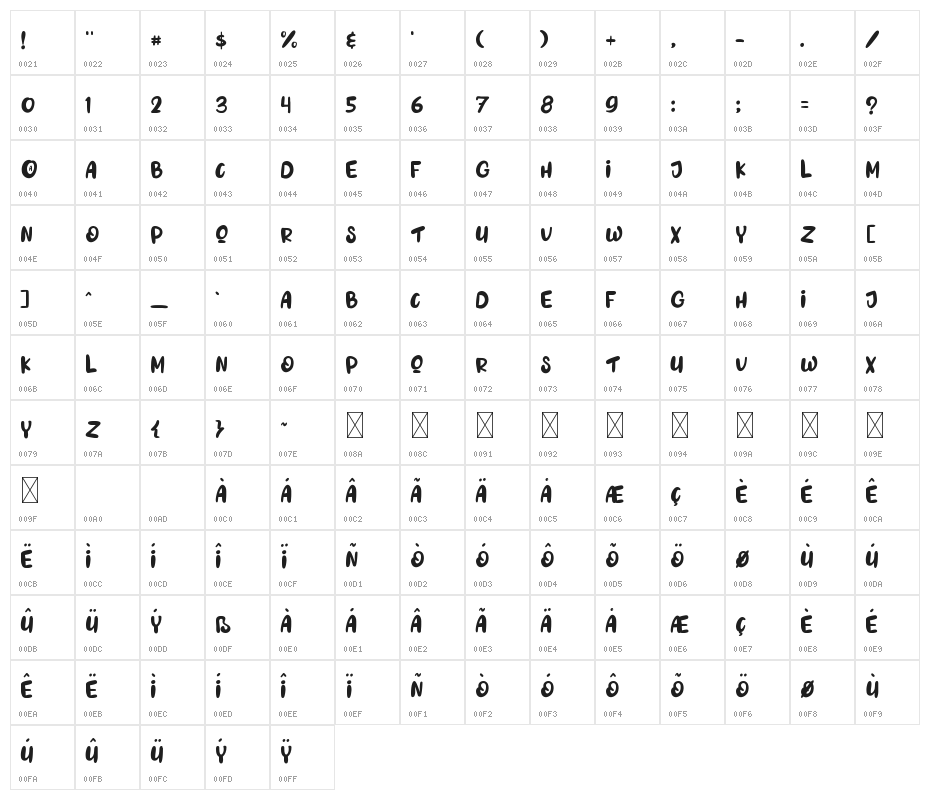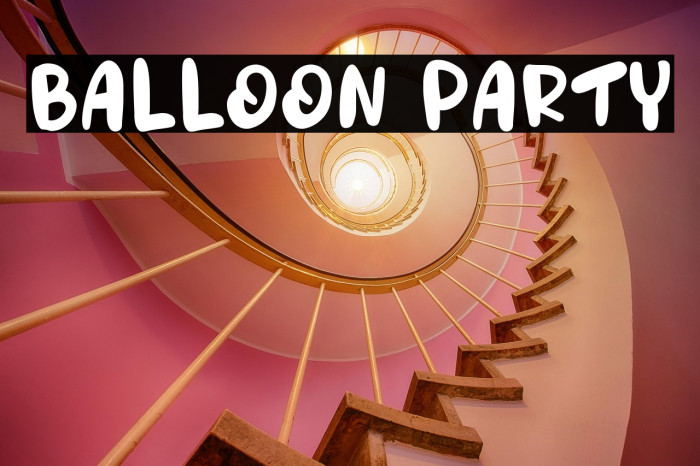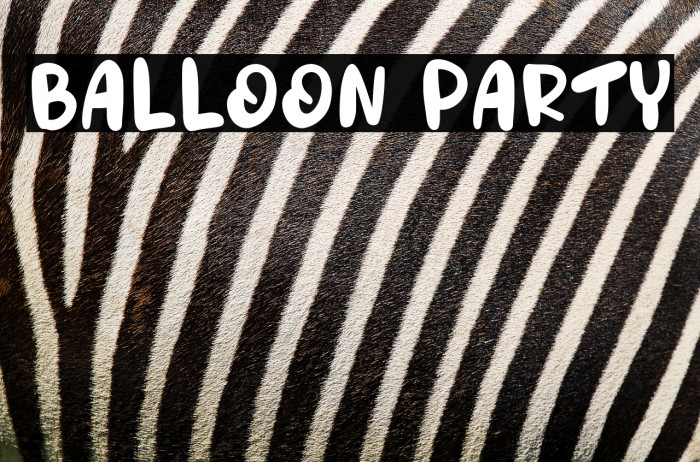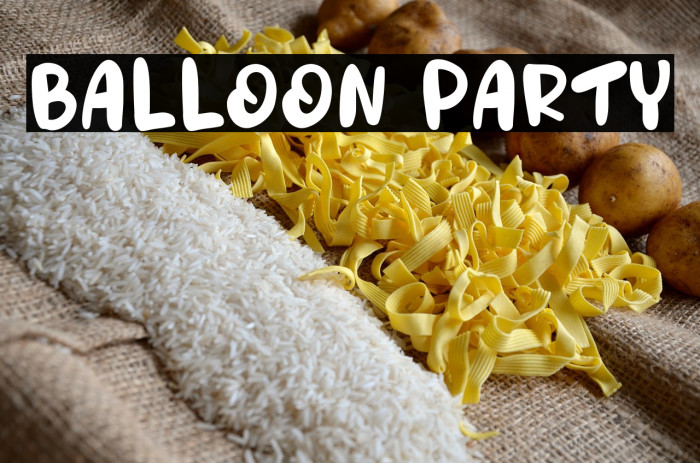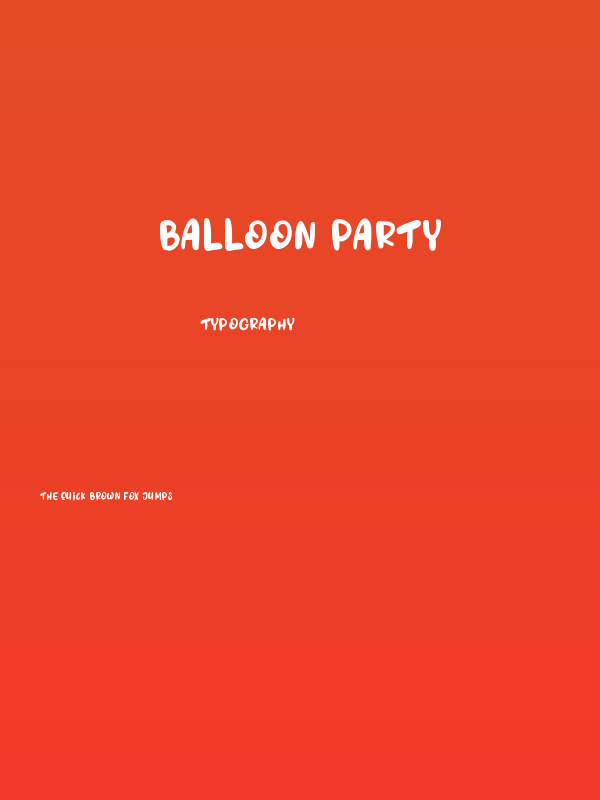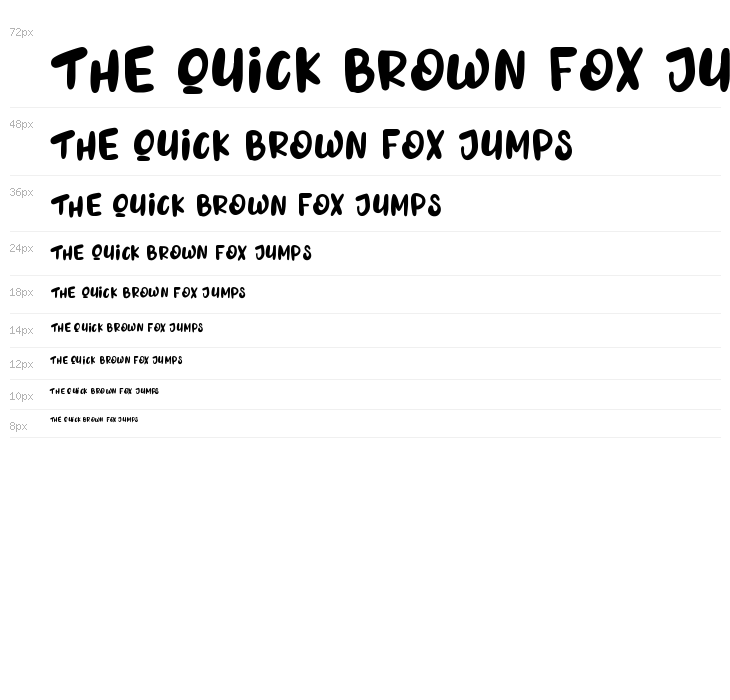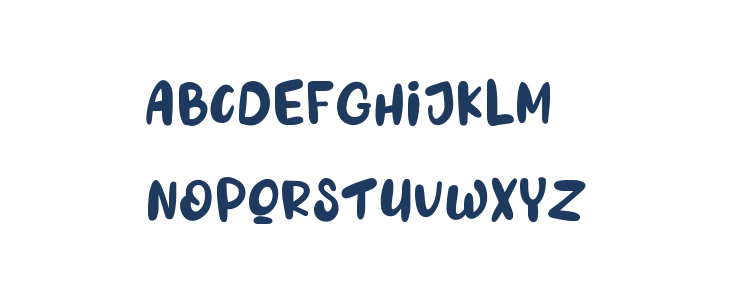
Balloon Party Font
| Stile generale | Playful, Whimsical |
| Progetti proposti | Ideal for children's books, party invitations, playful branding, and creative posters. |